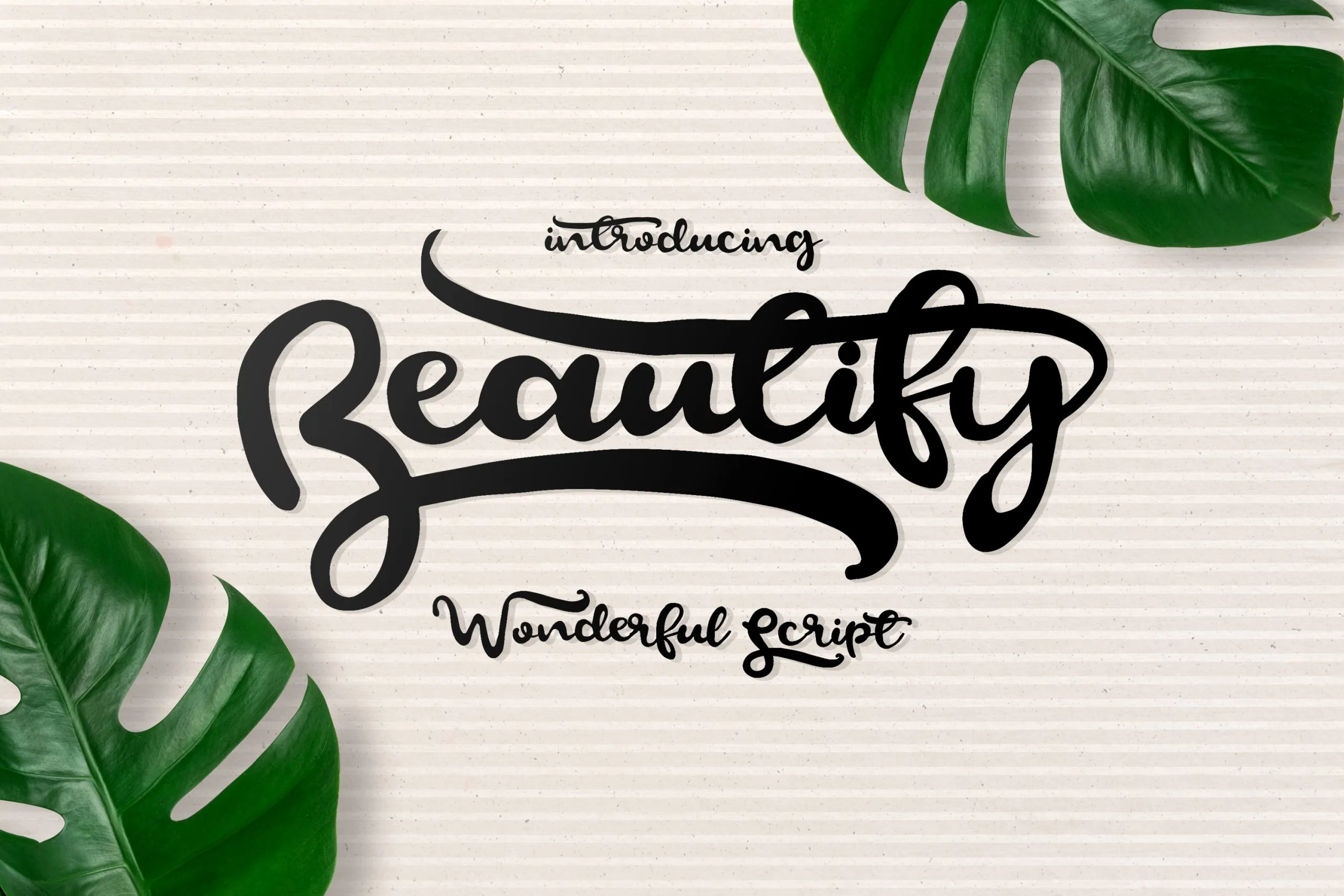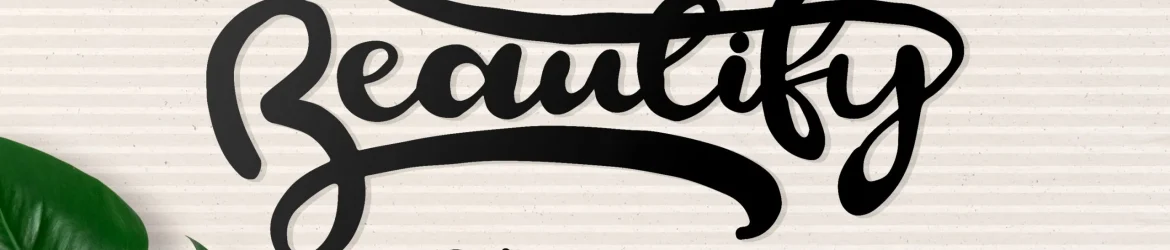
Beautify Script Font – Download Grátis
A fonte Beautify Script foi criada por Yasir Ekinci e é uma fonte premium que agora está disponível gratuitamente para download. A Beautify Script é uma fonte script, ótima para textos de estilo pessoal ou personalizados. Esse projeto gratuito oferece caracteres padrão e extras em várias línguas, garantindo uma ampla gama de usabilidade. Este tipo de texto criado à mão tem o poder de tornar qualquer documento único e sofisticado. Além disso, todos os usuários são agradecidos por apreciarem este projeto maravilhoso e seguirem Hamilton como fonte inspiradora.